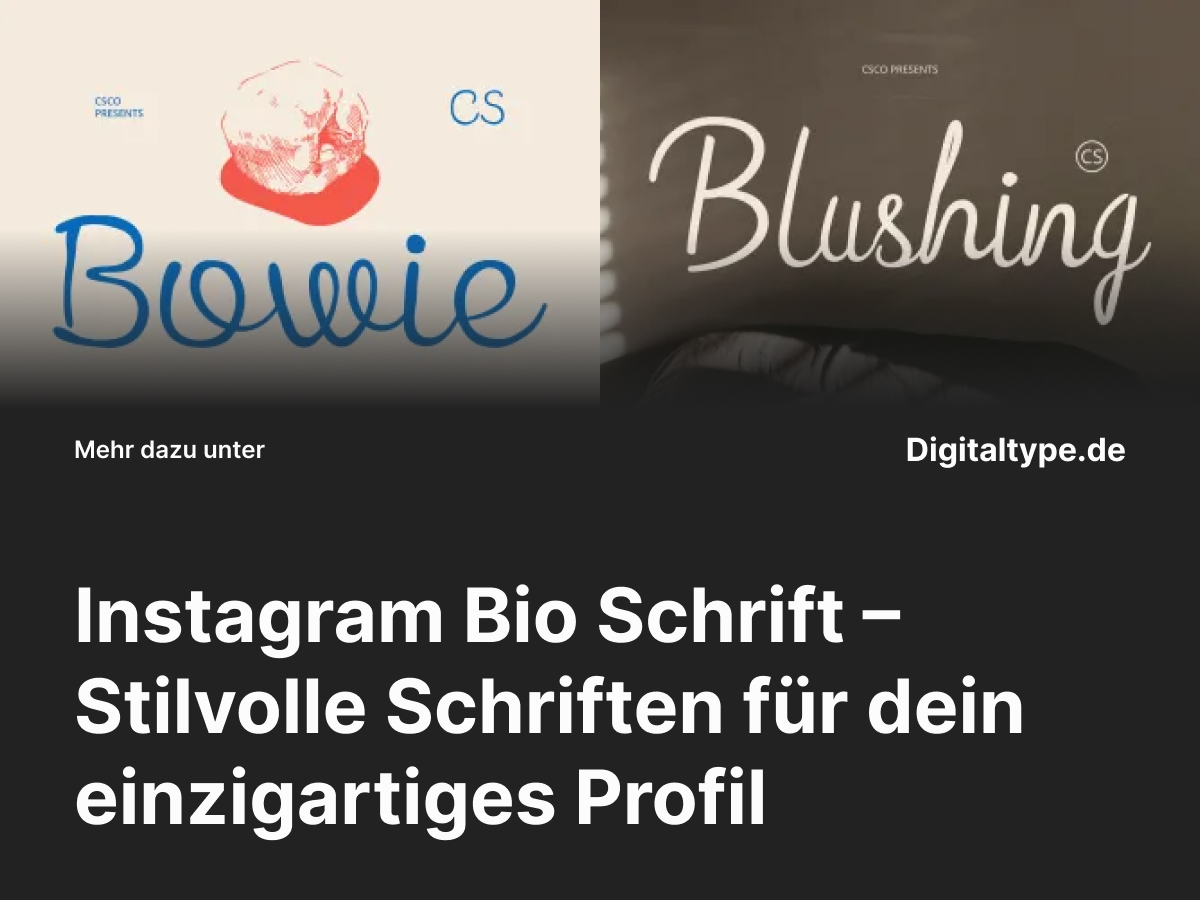
Deine Instagram-Bio ist deine digitale Visitenkarte – der erste Eindruck zählt!
Mit einer Instagram Bio Schrift kannst du deinen Stil ausdrücken, dich von anderen abheben und deinem Profil eine persönliche Note verleihen.
In diesem Artikel zeigen wir dir 6 wunderschöne Script-Schriften, die perfekt für Instagram-Bios, Social-Media-Designs und moderne Markenauftritte sind.
Was ist eine Instagram Bio Schrift?
Unter einer Instagram Bio Schrift versteht man Schriftarten, die speziell dafür verwendet werden, den Text in deiner Instagram-Bio individuell und stilvoll zu gestalten.
Während Instagram selbst keine Schriftanpassung erlaubt, kannst du über Schriftgeneratoren oder Design-Tools kreative Schriftarten verwenden, um dein Profil hervorzuheben.
Von eleganten Script-Fonts bis hin zu verspielten Handlettering-Schriften – die Auswahl ist riesig.
Ob du ein Influencer, Künstler oder Markeninhaber bist, die richtige Schrift kann deine Botschaft unterstreichen und Emotionen wecken.
Warum du eine besondere Schrift in deiner Instagram-Bio verwenden solltest
- 1. Einzigartigkeit: Hebe dich von Millionen anderer Profile ab.
- 2. Ausdruck deines Stils: Eine passende Schrift transportiert deine Persönlichkeit oder Markenidentität.
- 3. Professioneller Look: Mit einem abgestimmten Font wirkt dein Profil durchdachter und hochwertiger.
- 4. Emotionale Wirkung: Schriften vermitteln Gefühle – von elegant bis verspielt.
Eine Instagram Bio Schrift ist mehr als nur Textgestaltung – sie ist ein visuelles Statement.
Die 6 besten Instagram Bio Schriftarten für Social-Media-Stil
Hier findest du sechs exklusive Instagram Bio Schriftarten, die deinen Profiltext auf das nächste Level bringen.
Sie sind ideal für Bios, Story-Highlights, Zitate oder Branding-Projekte.
1. CS Bowie Script Font
Ein moderner, eleganter Script-Font mit glatten Schwüngen. Perfekt für stylische Bios, Modeprofile oder kreative Markenauftritte.
2. CS Blushing Script Font
CS Blushing bringt Romantik und Charme in deine Bio. Ideal für feminine Profile, Lifestyle-Accounts oder kreative Unternehmerinnen.
3. CS Belsy Script Font
Eine handgeschriebene Schrift mit sanftem Fluss. Perfekt für natürliche, authentische Marken, die Persönlichkeit zeigen wollen.
4. Galeiya Cute Script Font
Galeiya ist verspielt und charmant – ideal für kreative oder künstlerische Bios, die Freude und Energie ausstrahlen.
5. Manelyn Cute Script Font
Mit ihren runden Formen und weichen Linien eignet sich Manelyn hervorragend für freundliche und kreative Social-Media-Designs.
6. CS Alicent Script Font
CS Alicent vereint Eleganz und Lesbarkeit. Eine perfekte Wahl für Minimalisten und Creator, die Stil mit Klarheit kombinieren.
Design-Tipps für deine Instagram-Bio
- 1. Schrift passend zum Profil wählen: Elegant für Mode und Lifestyle, verspielt für Kreative, minimal für Profis.
- 2. Weniger ist mehr: Nutze 1–2 Schriftarten, um ein harmonisches Gesamtbild zu schaffen.
- 3. Emojis gezielt einsetzen: Kombiniere sie mit Schrift, um visuelle Highlights zu setzen.
- 4. Lesbarkeit prüfen: Achte darauf, dass dein Text auf allen Geräten klar erkennbar bleibt.
Fazit: Instagram Bio Schrift für kreative Profile
Mit einer Instagram Bio Schrift kannst du deiner Online-Präsenz Ausdruck verleihen und dich stilvoll präsentieren.
Ob elegant, romantisch oder modern – die richtige Schrift betont deinen Charakter und hebt deine Marke hervor.
Die vorgestellten Fonts bieten dir Inspiration und Stilvielfalt für dein persönliches oder professionelles Profil.
Egal ob Influencer, Designer oder Content-Creator – die richtige Typografie macht den Unterschied.